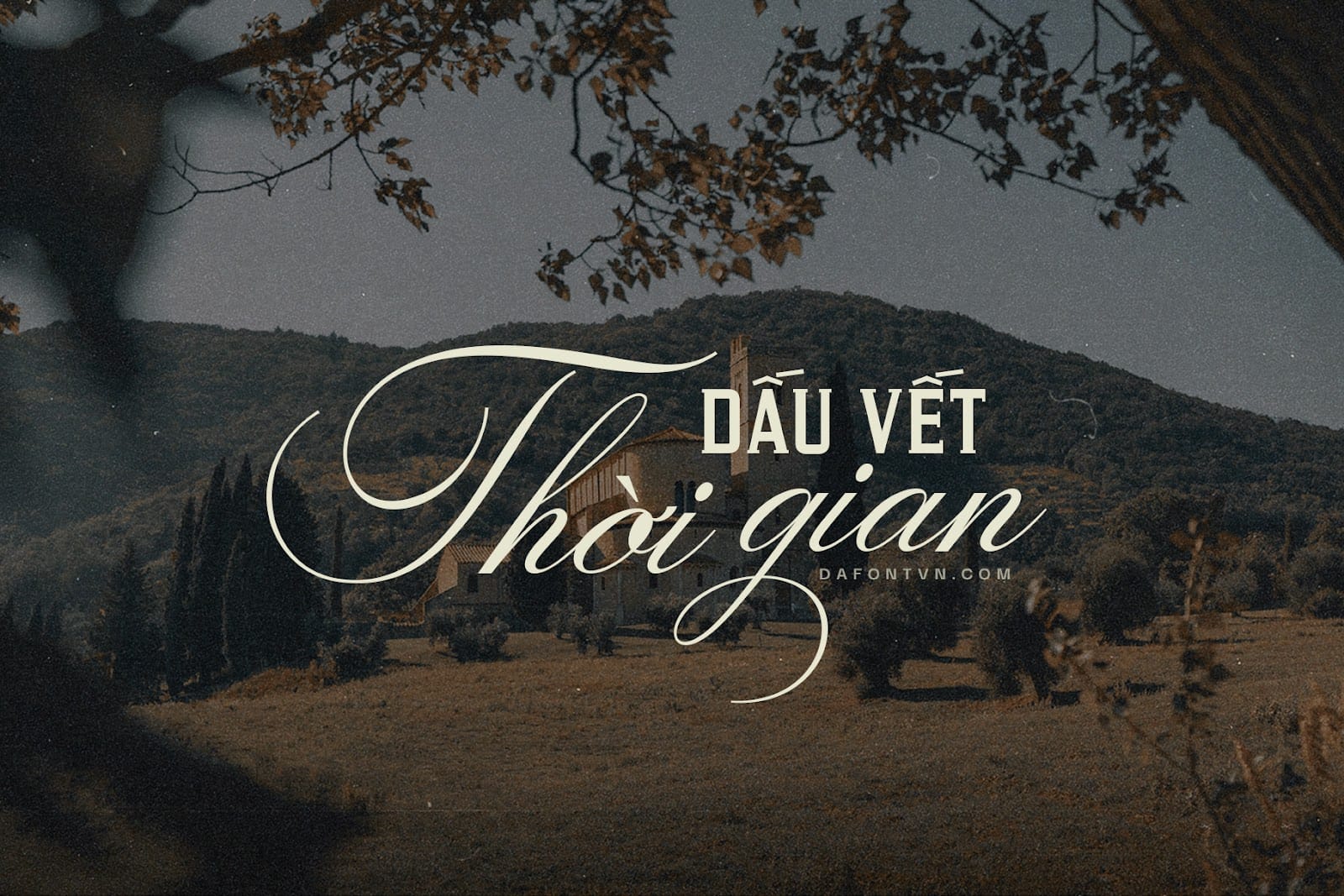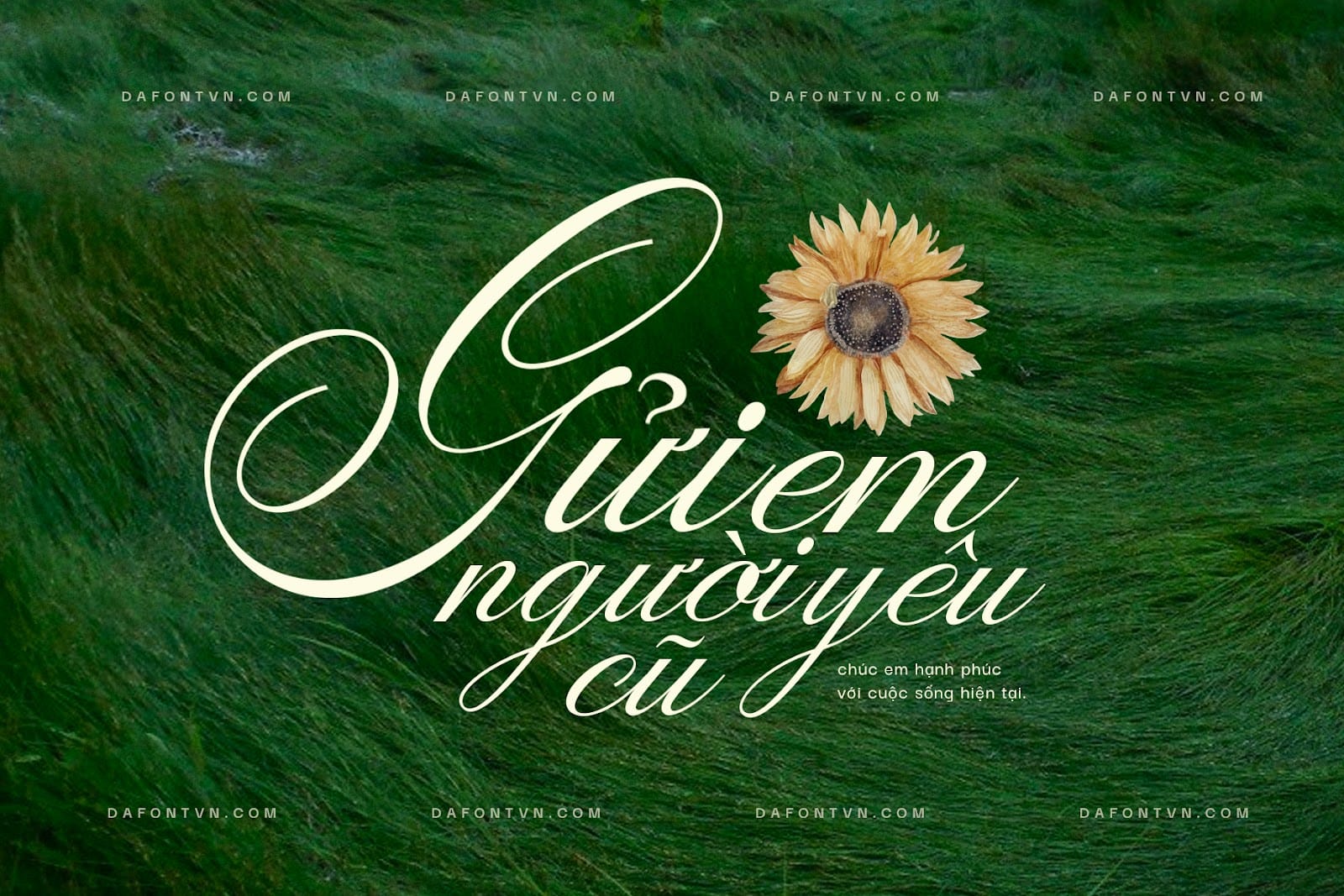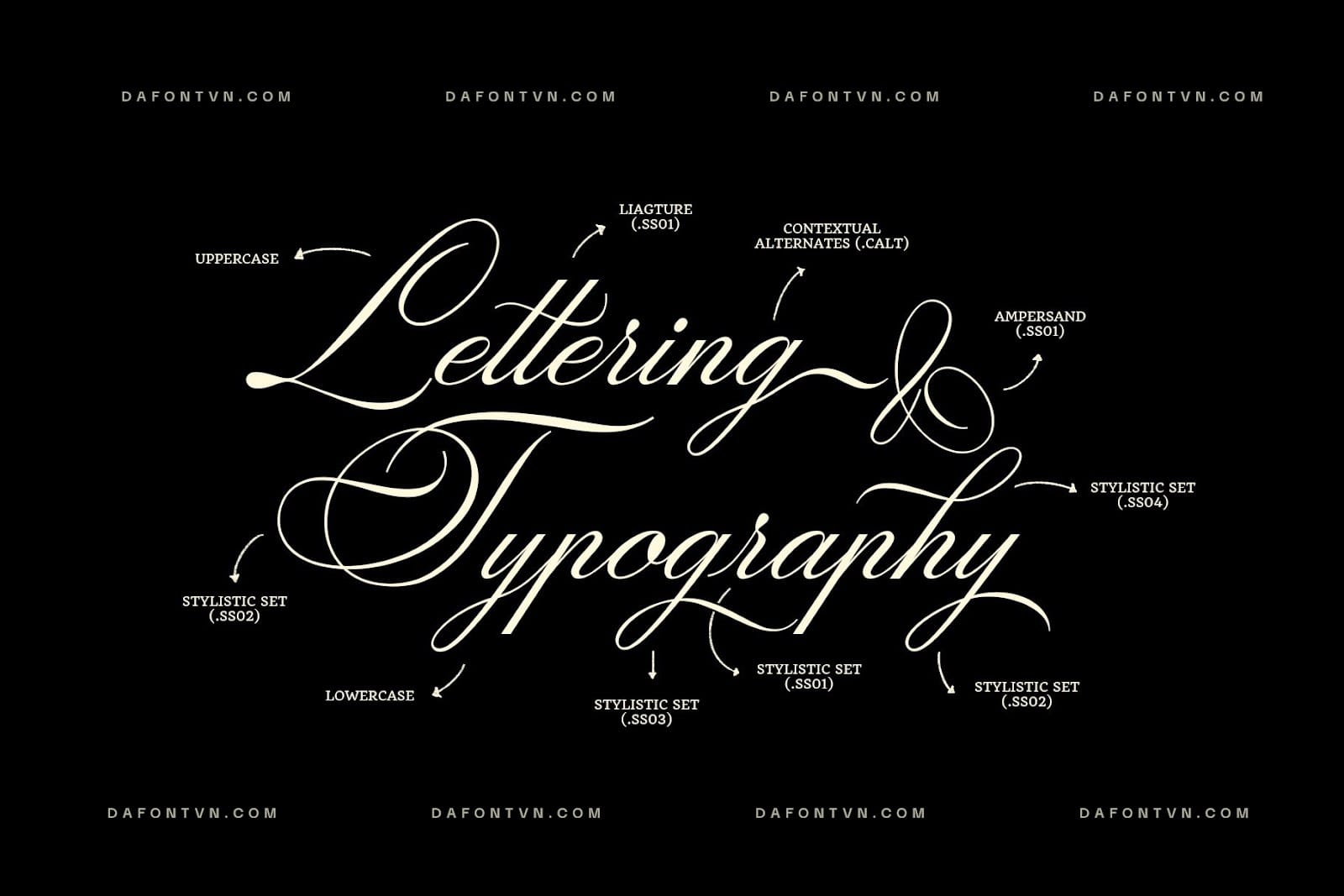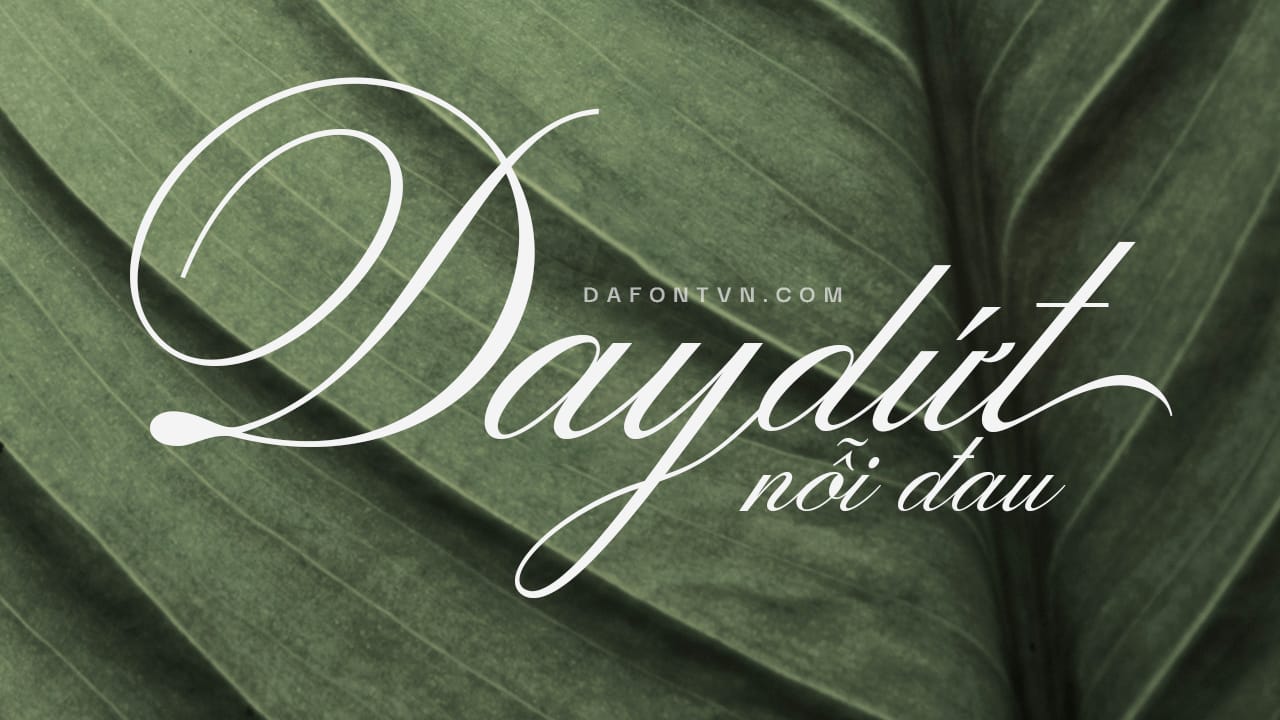
ED Drayton Font là một kiểu chữ viết tay tuyệt đẹp mang hơi hướng cổ điển với các nét chữ được thiết kế nghiêng độc đáo nhưng vẫn mang nhiều nét hiện đại. Phông chữ này bao gồm 535 glyph và với hơn 120 stylistic khác nhau vì vậy bạn có thể tùy biến các kiểu chữ để tạo ra các thiết kế độc đáo khác nhau.
Bên cạnh đó, font ED Drayton cũng được thiết kế dễ dàng để ghép với nhiều loại phông chữ khác nhau như các kiểu phông chữ serif. Phông chữ này hoàn hảo cho các dự án sáng tạo như xây dựng thương hiệu, logo, thư mời, bao bì, tạp chí, tiêu đề, thiết kế web, sách, thiệp mời, v.v.
Font ED Drayton Việt hóa hoàn chỉnh đã được tối ưu, kerning và chỉnh sửa lại 1 số dấu cho phù hợp hơn với font.